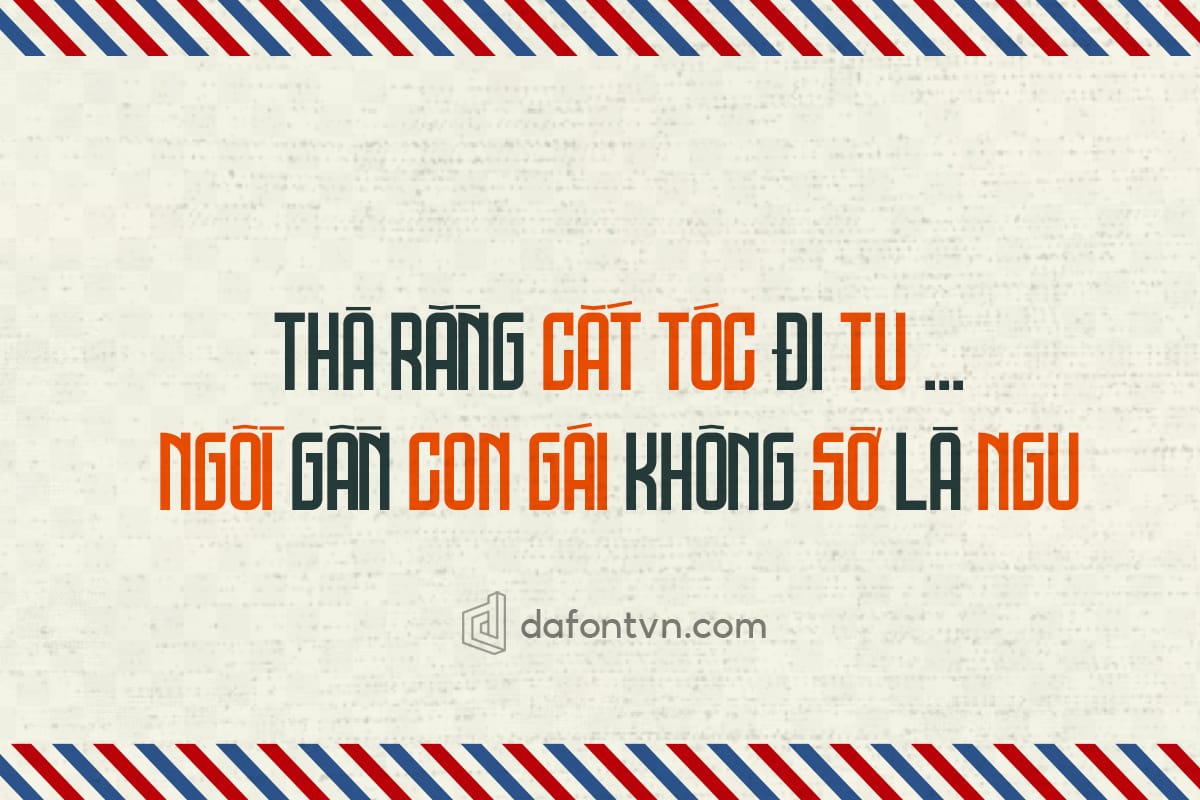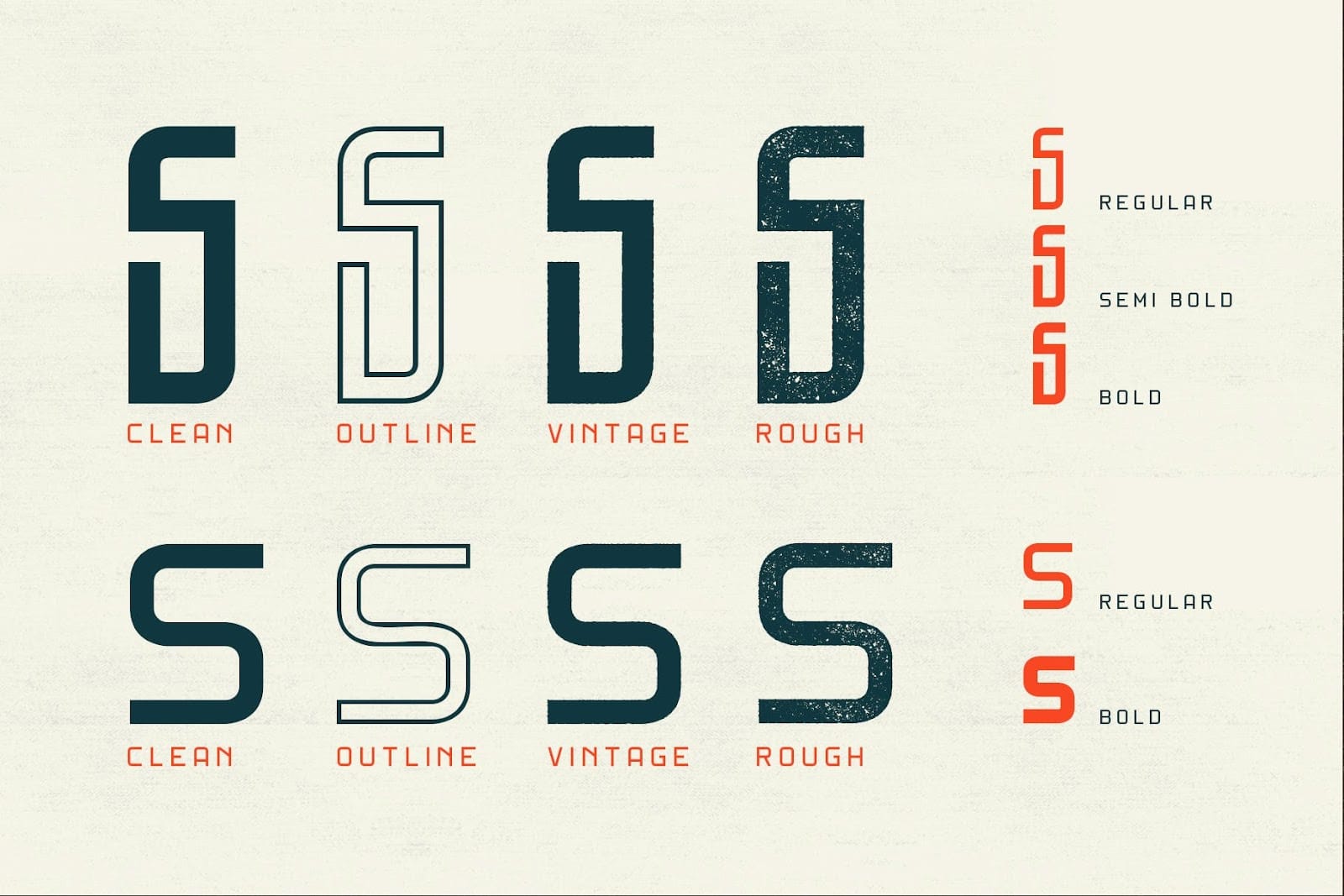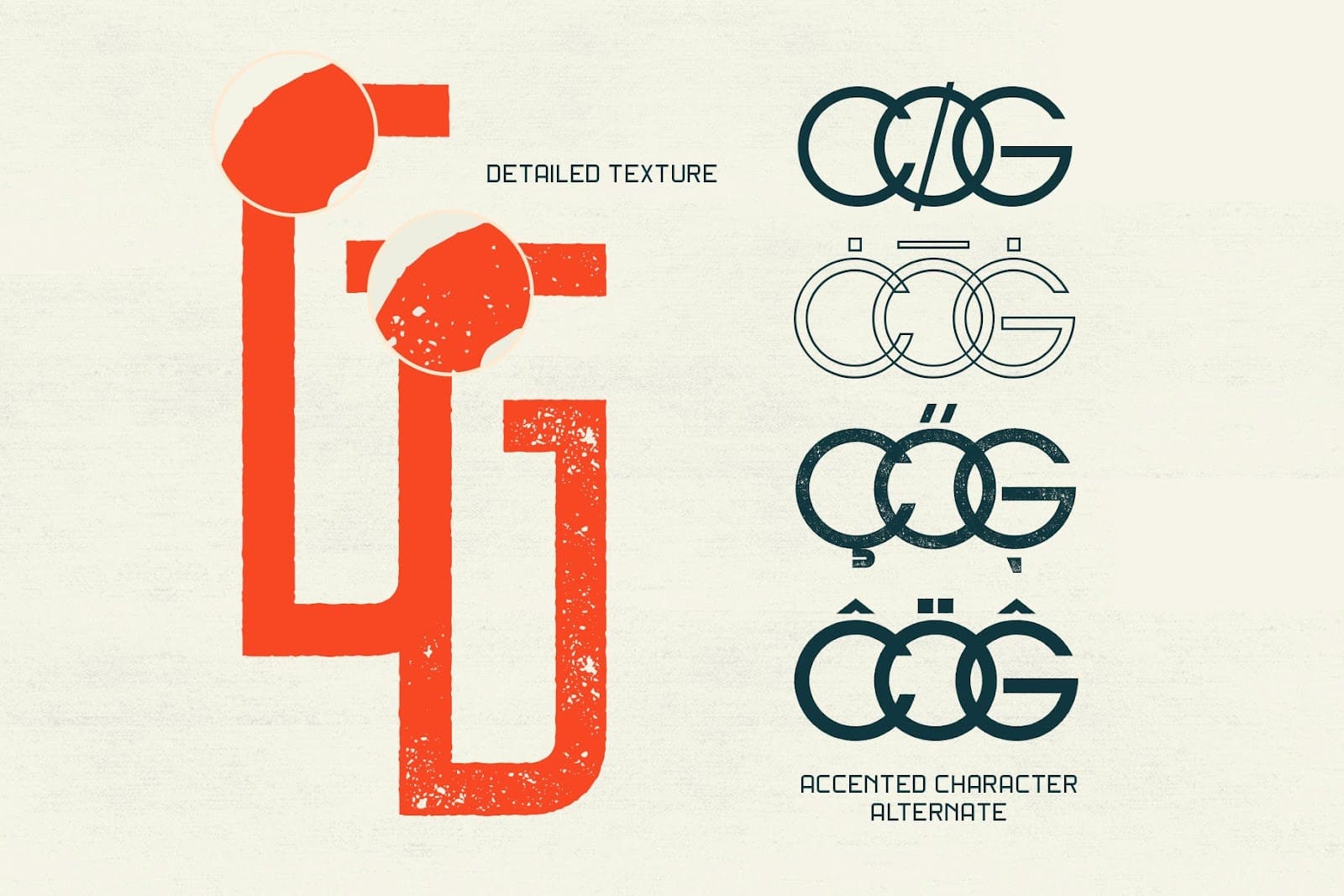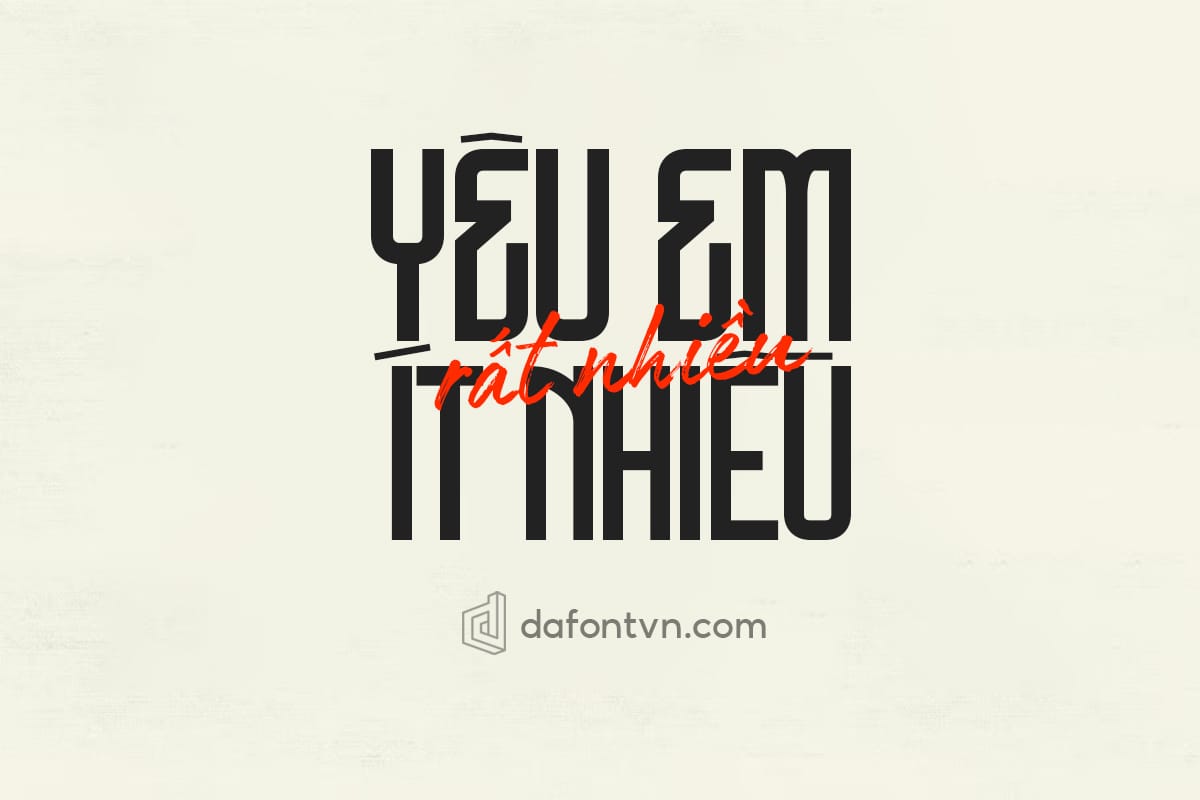
DNS Gibsons là bộ phông chữ khá chất lượng với các nét chữ được thiết kế cứng cáp và mạnh mẽ khá phù hợp cho các thiết kế cổ điển, vintage, retro… Bộ font gồm 4 font việt hóa đầy đủ, các dấu đã được thiết kế lại hoàn toàn so với bản gốc để font mang phong cách xưa cũ hơn.